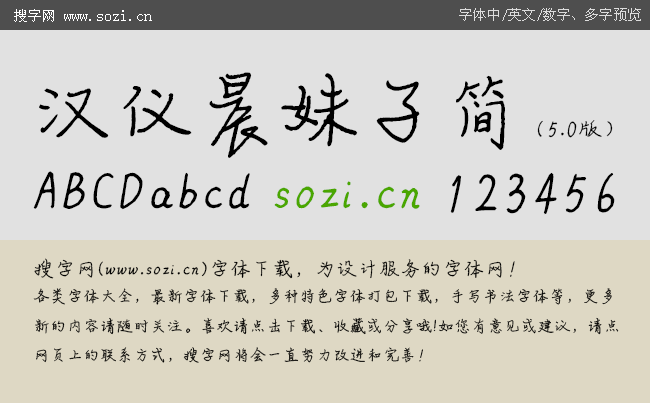
漢儀晨妹子簡(jiǎn)5.0版
漢儀晨妹子簡(jiǎn)5.0版是搜字網(wǎng)給大家提供一款漢儀字體公司出品的書(shū)法中文字體下載,這款字運(yùn)該款字體屬于手寫(xiě)體中的硬筆書(shū)法,好似像鄰家女孩手寫(xiě)的筆跡。相信你一定會(huì)喜歡在自己作品中用到這款中文字體!歡迎下載!